Ошибки в кириллическом курсиве, нарушающие ритм текста
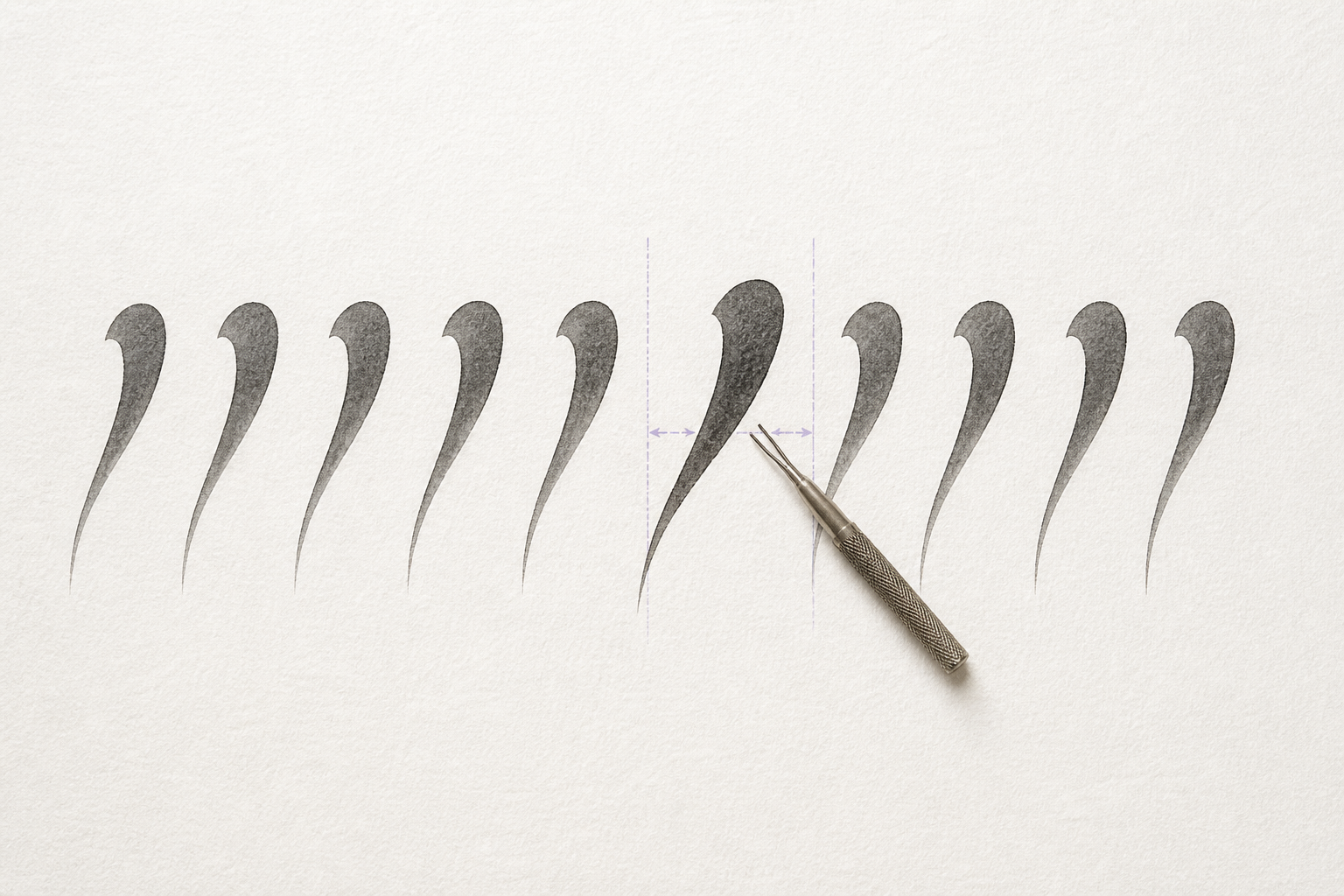
Ошибки в кириллическом курсиве нарушают ритм текста, когда буквы, интервалы и знаки препинания не образуют единую зрительную линию. Чаще всего проблема возникает из-за механического наклона прямого начертания, неудачных форм кириллических знаков, слабого кернинга и смешения разных принципов построения. Ниже — практический разбор, который поможет проверить курсивную гарнитуру и исправить её до публикации.
Почему кириллический курсив требует отдельной работы
Кириллица не является латиницей с заменёнными символами. У неё собственная система пропорций, характерные формы строчных и прописных букв, особые соединения, диакритика и знаки препинания. Поэтому качественный курсив создают не простым наклоном вертикальных букв, а как самостоятельное начертание: меняют ширину знаков, пластику штрихов, положение выносных элементов и расстояния между соседями.
Ритм текста — это равномерность чередования тёмных штрихов и светлых промежутков. В кириллическом курсиве он особенно заметен в длинных строках, где соседствуют буквы с разной шириной и наклоном. Если одна буква чрезмерно заваливается, другая остаётся почти прямой, а третья получает слишком узкий апрош, строка начинает выглядеть волнистой и утомляет при чтении.
Механический наклон прямого начертания
Самая распространённая ошибка — применить к прямому начертанию автоматический наклон и считать задачу решённой. Такой приём сохраняет вертикальную пластику знаков, но не учитывает, что курсив меняет зрительный вес, ширину и характер соединений. В результате буквы наклоняются одинаково, хотя их формы требуют разной компенсации, а круглые и угловатые элементы начинают конфликтовать друг с другом.
Например, у кириллических л, д и я наклон может визуально усиливаться из-за диагональных штрихов. Если оставить их ширину и положение неизменными, буквы начнут словно падать вправо. У о, с и е, наоборот, наклон часто выглядит слабее, поэтому рядом с ними появляются провалы в динамике строки. Хороший курсив балансирует эти различия, а не стирает их одной геометрической операцией.
Неподходящие формы кириллических букв
В курсивной кириллице важно различать не только наклон, но и конструкцию знаков. Особенно чувствительны строчные т, д, г, ф, л, я и б. Их форма должна соответствовать общему характеру гарнитуры и оставаться узнаваемой в малом кегле. Если буквы слишком близки к латинским аналогам или чрезмерно декоративны, чтение замедляется, а текст теряет нейтральный ритм.
Строчная т может быть построена по разным моделям: более традиционной, похожей на печатную форму, или более рукописной. Проблема возникает, когда выбранная модель не поддержана соседними буквами. Например, рукописная т рядом с геометричными и почти прямыми знаками выглядит чужеродно. Аналогично, слишком широкая д или тяжёлая ф меняют плотность слова и создают локальные тёмные пятна.
Буквы с диагоналями и округлыми формами
Диагональные буквы л, и, к, ж и я часто требуют оптической коррекции. Геометрически одинаковый наклон для них не означает одинаковый визуальный наклон: диагонали сами усиливают движение вправо. Округлые буквы о, с, е и ю, напротив, могут казаться более спокойными. Сравнивайте их в парах и словах, а не только по метрикам, чтобы увидеть, где строка ускоряется или проседает.
Ошибки в кернинге и боковых апрошах
Кернинг и боковые апроши определяют, как буквы взаимодействуют в конкретной паре и в потоке текста. В курсиве их настройка сложнее, потому что наклонные элементы заходят в соседнее пространство. Если полагаться только на автоматические значения, между буквами могут появиться лишние щели, а отдельные пары начнут слипаться.
Часто требуют ручной проверки пары с диагоналями и нависающими элементами: «Ла», «Та», «Го», «Ул», «Як», «Ку», «жн» и «тл». В заголовках проблема заметнее, поскольку крупный кегль увеличивает видимость каждого интервала. В основном тексте важнее общий темп: даже небольшая ошибка, повторяющаяся в каждой строке, становится устойчивым визуальным раздражителем.
Проверяйте не только расстояние между чёрными формами, но и объём белого пространства вокруг них. В паре «го» промежуток может казаться слишком узким из-за округлых очертаний, а в «ла» — слишком широким из-за диагонали и наклона. Оптический кернинг не обязан совпадать с математическим: цель состоит в равномерном восприятии, а не в одинаковых числовых интервалах.
Пунктуация, кавычки и цифры в наклонном тексте
Курсивный текст часто выглядит неровным не из-за букв, а из-за знаков препинания. Запятые, точки, двоеточия, скобки и кавычки имеют собственную оптическую массу. Если они остаются строго вертикальными или, наоборот, получают чрезмерный наклон, строка распадается на разные визуальные режимы. Знаки должны поддерживать движение текста, но не превращаться в декоративные акценты.
Отдельно проверяйте русские кавычки «ёлочки», тире и скобки. У кавычек важны угол, высота и расстояние до соседней буквы; у тире — длина и положение относительно строки. В фразе «типографический ритм — это баланс» тире не должно выглядеть тяжелее соседних слов. Скобки не должны визуально закрывать слово или создавать слишком большие пустоты перед знаками.
Цифры в курсиве также требуют согласованности. Если текстовое начертание наклонено, а цифры остаются прямыми, это допустимо только при осознанной системе. Иначе дата, размер или номер пункта будут выпадать из строки. Проверьте сочетания «12 пунктов», «2026 год», «3:2» и диапазоны с тире: цифры должны сохранять читаемость и не образовывать случайные провалы между буквами.
Смешение разных моделей курсива
В одной гарнитуре иногда смешиваются несколько представлений о курсиве: спокойный редакционный наклон, рукописная пластика и почти каллиграфический вариант. Каждая модель может быть выразительной сама по себе, но их соседство без системы нарушает иерархию. Пользователь перестаёт понимать, где выделение, где часть шрифтового характера, а где случайная форма знака.
Типичный пример — сочетание геометричных прописных с мягкими рукописными строчными. В слове «Культура» первая буква выглядит как наклонная версия прямого начертания, а остальные напоминают письмо пером. Такой контраст может быть художественным при намеренной стилизации, но для статьи, интерфейса или длинного текста чаще становится источником шума. Сначала выберите принцип, затем последовательно примените его ко всему набору.
Как проверить ритм кириллического курсива на практике
Проверка должна проходить на нескольких уровнях: отдельные знаки, пары, слова, строки и реальные текстовые фрагменты. Сначала убедитесь, что базовые буквы имеют ясную конструкцию. Затем оцените, как меняется плотность в словах с диагоналями, округлыми формами, выносными элементами и повторяющимися штрихами. После этого посмотрите на абзац целиком: ритм проявляется именно в последовательности строк.
- Соберите тестовую строку из часто встречающихся кириллических сочетаний: «ла», «ли», «та», «то», «го», «же», «ня», «ри».
- Проверьте слова разной плотности: «галерея», «типографика», «шрифтовой», «дизайн», «выразительность».
- Сравните строчные, прописные, цифры и знаки препинания в одном текстовом блоке.
- Увеличьте кегль и найдите заметные провалы в кернинге, затем уменьшите его до размера обычного чтения.
- Прочитайте несколько строк вслух и одновременно смотрите на движение букв: визуальные остановки часто совпадают с неудачными интервалами.
- Проверьте курсив в заголовке, подписи, основном тексте и коротком выделении, потому что разные размеры выявляют разные дефекты.
Полезно тестировать не только идеальные слова, но и реальные материалы: заголовок статьи, лид, список, подпись к изображению, дату и короткую кнопку. В каждом формате меняется масштаб и плотность. Начертание, которое хорошо смотрится в одном слове, может оказаться слишком рыхлым в абзаце или слишком тяжёлым в крупном заголовке.
- Использовать автоматический наклон вместо отдельного курсивного начертания. Исправление: переработать формы, ширины и наклон с учётом кириллической конструкции.
- Настраивать только латинские пары. Исправление: составить отдельный список кириллических сочетаний и проверить его вручную.
- Игнорировать строчную т. Исправление: выбрать модель буквы заранее и сопоставить её с пластикой д, м, н, п и ш.
- Оставлять пунктуацию из прямого начертания без проверки. Исправление: оценить кавычки, скобки, тире и запятые в реальных фразах.
- Оценивать курсив по одному слову. Исправление: смотреть на абзацы, заголовки и многострочные блоки.
- Смешивать наклон, рукописность и декоративность без иерархии. Исправление: определить роль курсива и придерживаться одной визуальной логики.
- Проверять только крупный размер. Исправление: тестировать начертание в малом кегле, где особенно заметны неясные формы и тесные интервалы.
Чеклист перед выпуском шрифта или макета
Перед публикацией полезно пройти короткий контрольный список. Он не заменяет полноценную корректуру шрифта, но помогает обнаружить дефекты, которые нарушают читаемость уже на уровне макета. Особенно внимательно проверяйте места, где курсив используется для смыслового выделения: там неровности становятся заметнее из-за контраста с прямым начертанием.
- Проверьте, что курсив не является простым наклоном прямого начертания.
- Сравните наклон и вес букв с диагоналями, округлыми формами и вертикальными штрихами.
- Оцените формы строчных т, д, г, ф, л, я и б в словах, а не только отдельно.
- Настройте кернинг для кириллических пар и проверьте боковые апроши.
- Согласуйте кавычки, тире, скобки, запятые, точки и другие знаки с пластикой букв.
- Проверьте цифры, даты, размеры и диапазоны в составе русского текста.
- Посмотрите на курсив в малом, среднем и крупном кегле.
- Сравните абзац целиком: светлые промежутки должны распределяться равномерно.
- Убедитесь, что курсив сохраняет узнаваемость и не превращается в декоративный шифр.
Когда курсив лучше заменить другим способом выделения
Курсив не обязан использоваться в каждом случае, где нужно выделить слово. Если кириллическое начертание пока нестабильно или плохо читается в основном тексте, безопаснее применить полужирное начертание, изменение размера, цветовой акцент или отдельный стиль заголовка. В интерфейсах и справочных материалах приоритетом остаются скорость сканирования и однозначность букв.
Однако замена не должна маскировать проблему шрифта. Если курсив нужен для цитат, терминов, подписей или брендовой интонации, его следует доработать как полноценную часть системы. Хорошее решение определяется не выразительностью отдельной буквы, а тем, насколько стабильно начертание работает в разных размерах, языковых фрагментах и сочетаниях с прямым текстом.
Можно ли сделать кириллический курсив простым наклоном шрифта?
Технически это возможно, но результат обычно уступает отдельному курсивному начертанию. Механический наклон не исправляет формы букв, боковые апроши, кернинг и положение знаков препинания. Для короткой декоративной надписи такой приём иногда допустим, но для статьи, интерфейса или шрифтовой системы он часто нарушает ритм и читаемость.
Какие кириллические буквы чаще всего создают проблемы?
Особого внимания обычно требуют строчные т, д, г, ф, л, я и б, а также буквы с диагоналями — л, и, к, ж. Их конструкция сильно влияет на направление движения строки и плотность слова. Но проверять нужно весь набор: проблема может возникнуть в любой паре, особенно рядом с кавычками, скобками и цифрами.
Почему курсив выглядит неровно в заголовке, но нормально в тексте?
В крупном размере становятся заметны интервалы, углы и различия в толщине штрихов, которые теряются в малом кегле. Кроме того, заголовок часто содержит короткие слова с крупными буквами и нестандартными парами. Поэтому курсив нужно тестировать в нескольких размерах и отдельно корректировать сочетания, которые часто встречаются в заголовках.
Нужно ли наклонять кавычки и цифры вместе с буквами?
Единого обязательного правила нет: решение зависит от конструкции гарнитуры и её типографической задачи. Важно, чтобы знаки не выглядели случайно вставленными из другого начертания. Проверьте их в реальных фразах, датах и числовых сочетаниях, а затем выберите вариант, который сохраняет читаемость и общий ритм.
Как проверить курсив без специальных инструментов?
Наберите несколько строк с частотными кириллическими словами, увеличьте и уменьшите размер, затем сравните плотность букв и белых промежутков. Полезно смотреть на абзац издалека, читать его вслух и проверять места перехода между прямым и наклонным начертанием. Такой просмотр не заменяет редактор шрифтов, но быстро выявляет очевидные дефекты.
Всегда ли курсив должен быть сильно наклонён вправо?
Нет. Угол наклона определяется характером гарнитуры, шириной букв и задачей начертания. Слишком сильный наклон может ухудшить читаемость и усилить ощущение падения строки, а слишком слабый — не отличаться от прямого текста. Важнее не величина угла сама по себе, а согласованность форм, веса и интервалов.
Качественный кириллический курсив строится как самостоятельная система, где форма букв, наклон, вес, кернинг, апроши и пунктуация работают вместе. Главный критерий — ровный ритм строки и уверенная читаемость, а не эффектность отдельных знаков. Проверьте кириллицу в реальных словах и абзацах, устраните локальные провалы и только после этого используйте начертание в макете.